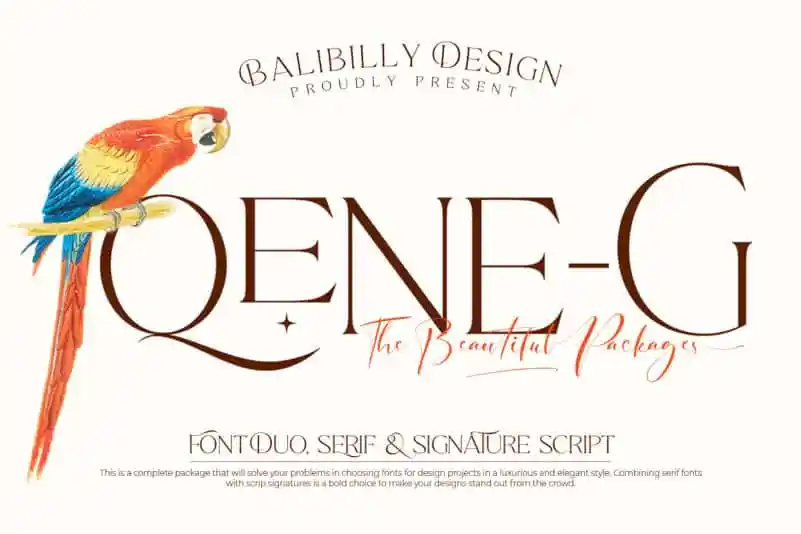
Qene-G Serif Font – Fonte Grátis
Qene-G Serif Font
Aqui está uma descrição envolvente para a página de download da fonte Qene-G Serif Font: Estamos encantados com a nova adição à sua biblioteca de fontes, a Qene-G Serif Font. Inspirada no problema que muitos designers enfrentam ao combinar diferentes tipografias em trabalhos gráficos, esta fonte é um consolidação eficaz e sofisticada. Qene-G serif foi criado por Balibilly Design, com uma proposta clara de unificar estilos sem perder a identidade única de cada elemento. Perfeita para projetos que exijam elegância e profundidade em suas letras, esta fonte se adapta perfeitamente aos mais variados formatos e ambientes digitais. Ideal tanto para criações sofisticadas quanto para design editorial ou layouts de site, a Qene-G Serif é uma escolha inteligente para quem busca um equilíbrio entre estilo e versatilidade. Combinada com outros tipos de fontes na sua coleção, ela vai garantir que seus designs não fiquem sem sal. Completando nossa oferta de fontes serif, a Qene-G é mais uma opção perfeita para aqueles que valorizam o equilíbrio entre simplicidade e detalhe em suas obras. Sua forma clássica e elegante certamente irá fazer diferença nos seus projetos. Estamos ansiosos para ver como você usa a Qene-G Serif Font, seja ela em uma nova identidade visual ou no próximo projeto de design. Estendemos nosso apreço por cada designer que enriquece nossa comunidade com seu trabalho e criatividade.